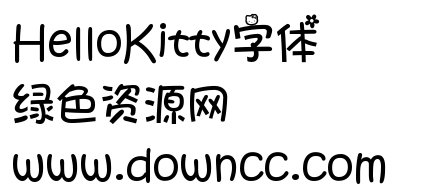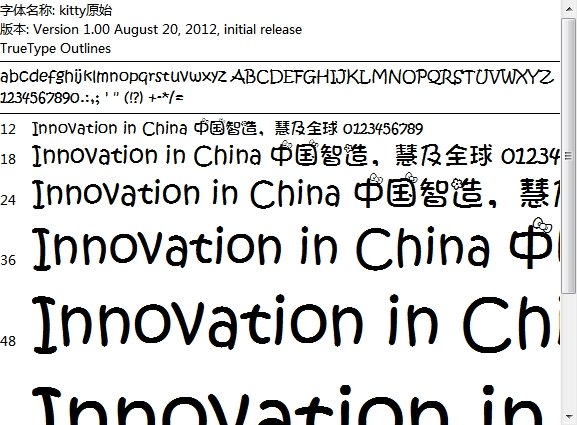
hellokitty字體是一款擁有著超級(jí)可愛(ài)點(diǎn)綴和修飾的藝術(shù)字體,炸裂你的少女心,活潑的蝴蝶結(jié),讓你的文字更加獨(dú)特,可以用來(lái)寫(xiě)日志、手帳哦!綠色資源網(wǎng)今日推薦!
HelloKitty是原始常規(guī)的中文字體,有著趣味的造型和點(diǎn)綴,讓字體也有萌萌噠的活潑和生趣,在綠色資源網(wǎng)下載即可擁有哦!
KITTY字體以pop字體為原形,在筆畫(huà)間嵌入大量的可愛(ài)卡通圖形,字體看起來(lái)俏皮可愛(ài),卡通味實(shí)足,感受滿滿的少女心和童真童趣!